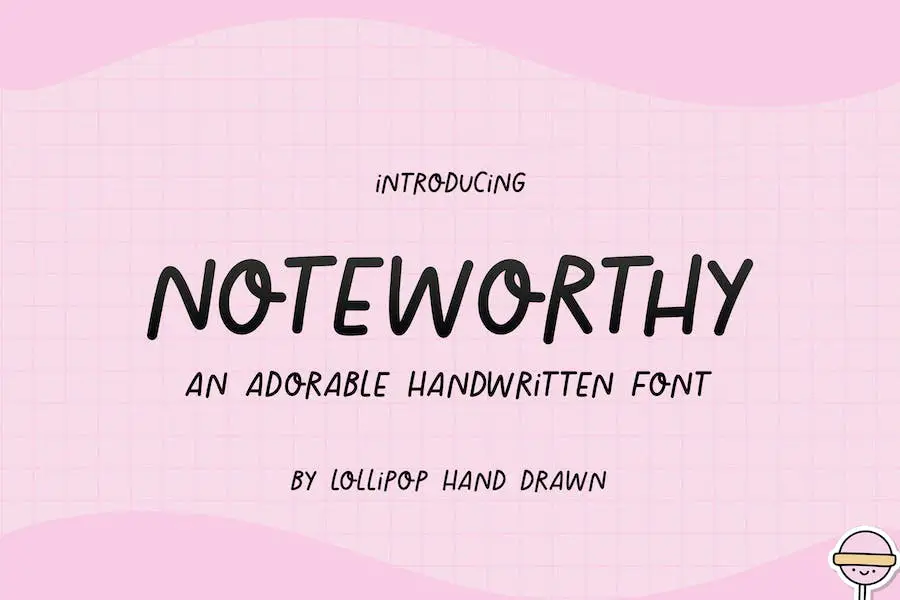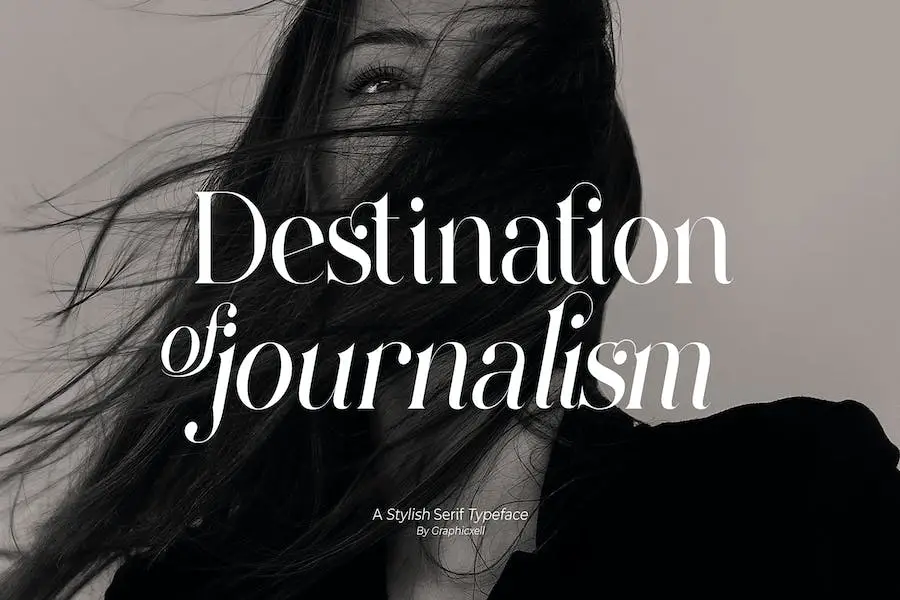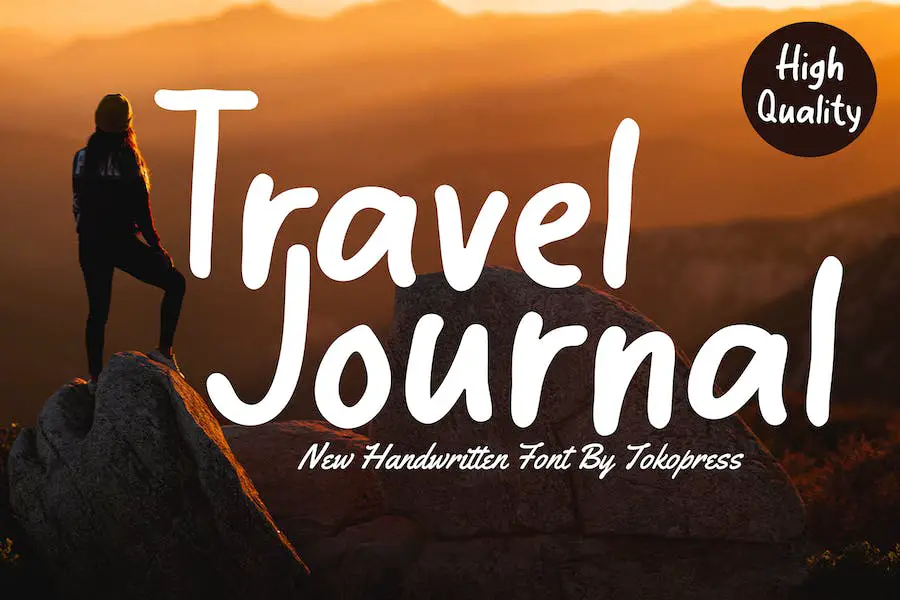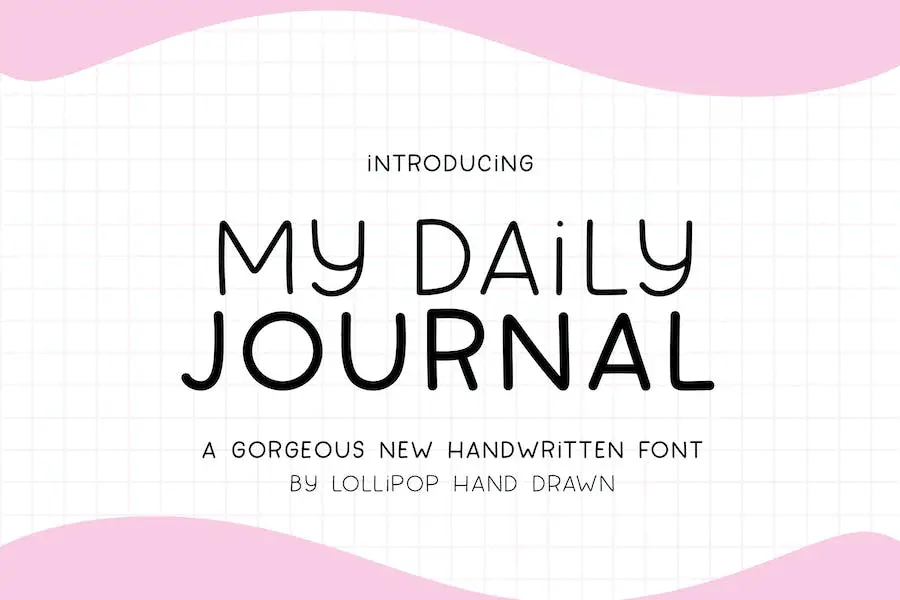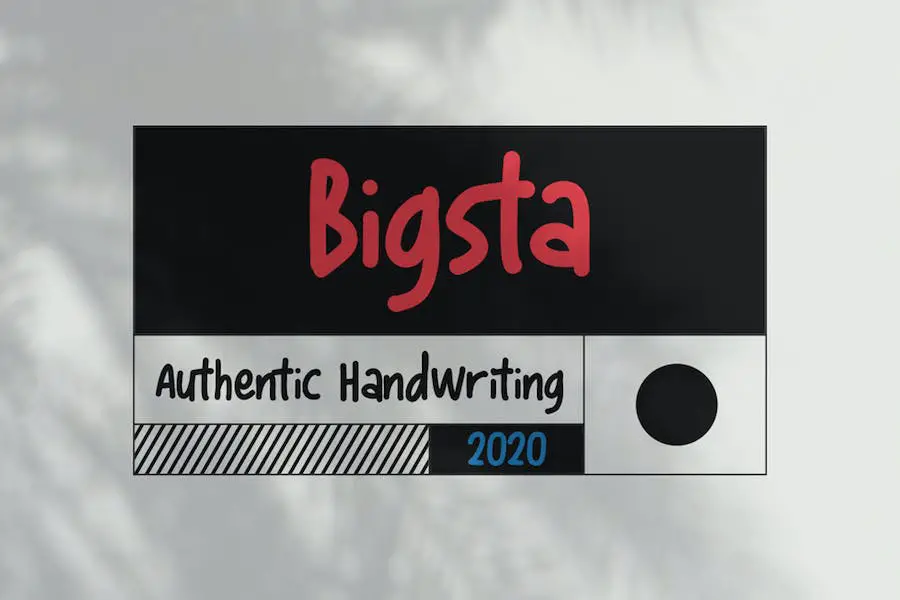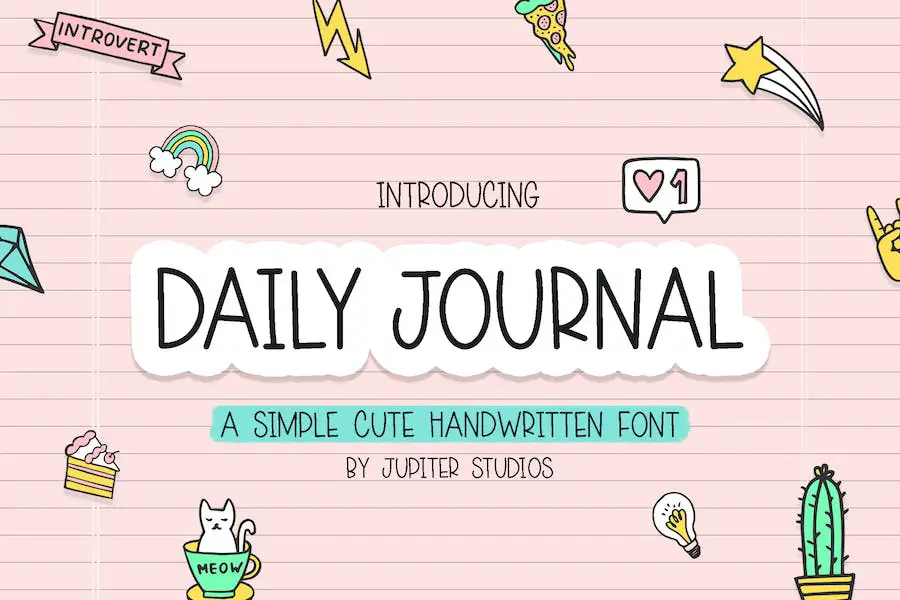
Cele mai bune 15 fonturi Bullet Journal 2023 (gratuit și premium)
Publicat: 2023-07-30Sunteți un designer grafic și doriți să îmbunătățiți designul proiectelor dvs. cu fontul perfect? Nu mai căuta! În această postare pe blog, vom explora cele mai bune 15 fonturi bullet journal care vă vor duce cu siguranță designurile la următorul nivel.
Dar mai întâi, s-ar putea să vă întrebați, ce face ca un font să fie „cel mai bun” pentru un jurnal bullet?
Ei bine, titlul acestei postări pe blog spune totul – cele mai bune 15 fonturi bullet journal! Și crede-mă, aceste fonturi nu sunt doar fonturile tale obișnuite. Au fost îngrijite și selectate cu atenție pe baza popularității, versatilității și atractivității lor estetice.
De fapt, știai că un font bine ales poate avea un impact semnificativ asupra designului general și lizibilitatea jurnalului tău bullet?
Statisticile și faptele sunt întotdeauna fascinante, așa că iată o mică informație pentru tine: conform unui sondaj recent, 87% dintre designerii grafici cred că tipografia joacă un rol crucial în succesul design-urilor lor.
Și odată cu popularitatea tot mai mare a jurnalului bullet, nu este de mirare că găsirea fontului perfect a devenit o prioritate de vârf pentru mulți designeri.
Acum că știți importanța alegerii fontului potrivit, să ne aruncăm în lista noastră cu cele mai bune 15 fonturi bullet journal. De la scripturi elegante și sofisticate până la sans serifuri îndrăznețe și moderne, avem un font pentru fiecare stil și preferință.
Așadar, fie că creați un spread săptămânal minimalist sau un tracker vibrant, veți găsi cu siguranță fontul perfect pentru a vă îmbunătăți experiența de jurnalizare bullet.
Cele mai bune fonturi Premium Bullet Journal
Îmbunătățiți designul bullet Journal cu aceste fonturi premium care vă vor duce proiectele la următorul nivel. Nu ratați să descoperiți fontul perfect pentru eforturile dvs. creative – explorați selecția de mai jos și deblocați posibilități infinite de design.
Melon Kundang
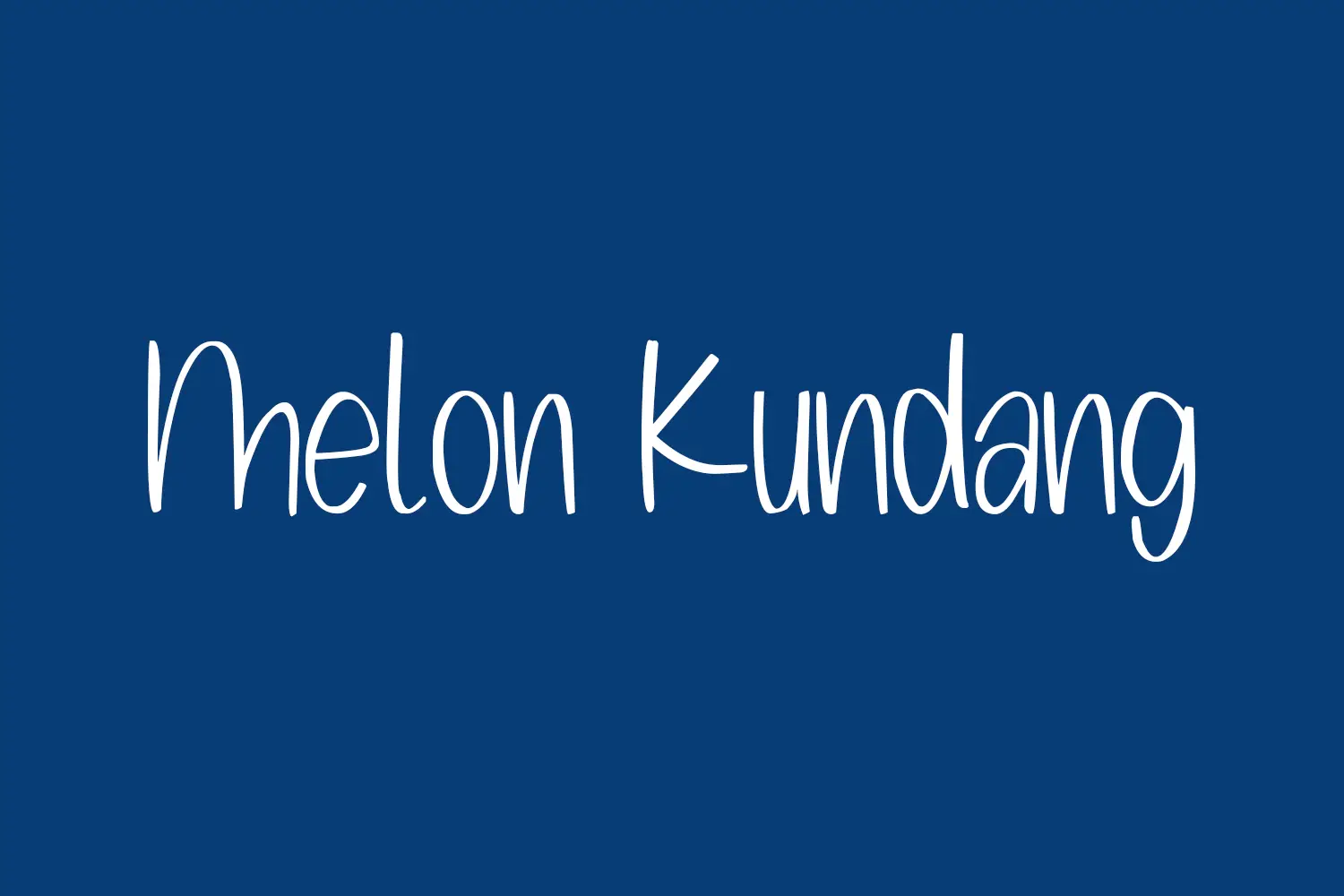
Melon Kundang este un font conceput special pentru designerii grafici care doresc să îmbunătățească designul proiectelor lor. Acest font drăguț bullet journal, creat de zamjump, adaugă o notă de personalitate și creativitate oricărui design.
Unul dintre atributele remarcabile ale Melon Kundang este natura sa jucăușă și capricioasă. Marginile rotunjite și curbele netede conferă acestui font o senzație prietenoasă și accesibilă, făcându-l perfect pentru proiecte uşoare sau adăugând o notă de farmec jurnalului tău.
Nu numai că Melon Kundang este atrăgător din punct de vedere vizual, dar este și foarte lizibil. Liniile curate și caracterele bine definite asigură că textul tău este ușor de citit, chiar și la dimensiuni mai mici.
Indiferent dacă îl folosiți pentru anteturi, paragrafe sau subtitrări, acest font se va asigura că conținutul dvs. este clar și captivant.
Palmiva
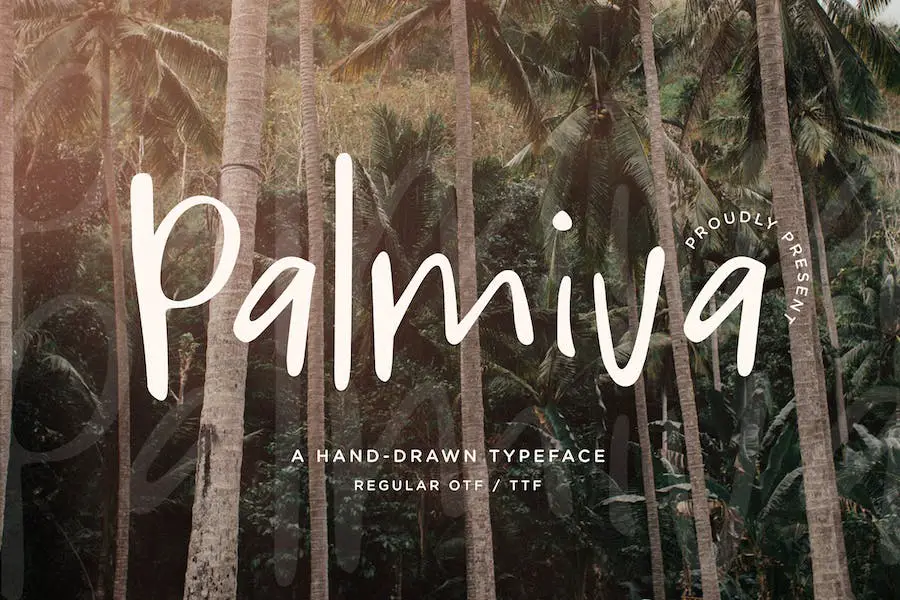
Palmiva este un font elegant desenat manual, care este creat cu atenție pentru a deveni un adevărat favorit pentru designerii grafici. Acest font este perfect pentru a adăuga o notă de eleganță și creativitate oricărui proiect.
Indiferent dacă lucrați cu fundaluri aglomerate sau aveți nevoie de un titlu remarcabil, Palmiva va arăta remarcabil și va îmbunătăți estetica generală a design-urilor dvs.
Stilul său unic și atenția la detalii îl fac o alegere de top pentru cei care doresc să-și ridice jurnalul bullet sau orice alt proiect de design. Cu Palmiva, munca ta va emana farmec și sofisticare, atrăgând fără efort atenția publicului tău.
Unic Tu
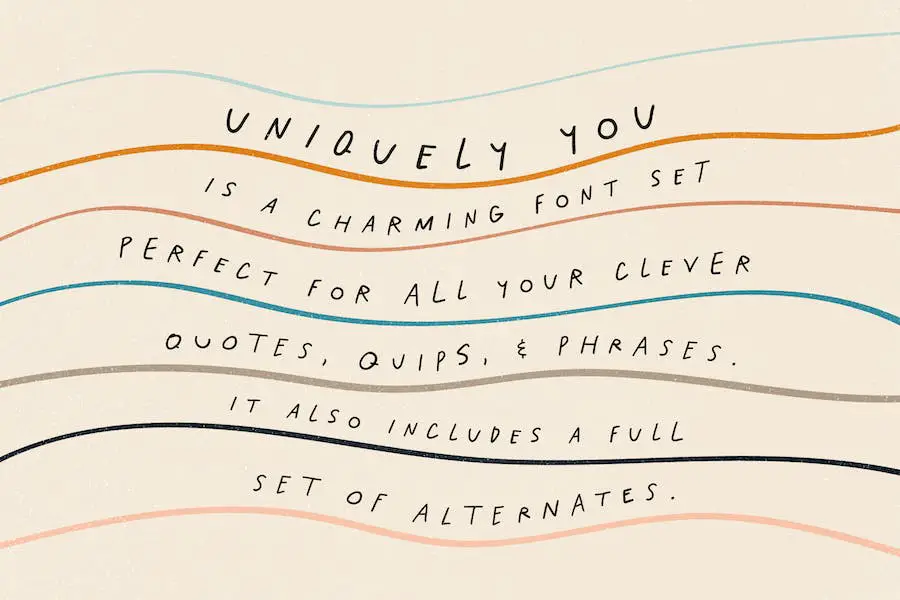
Uniquely You este un tip de literă jucăuș, desenat de mână, perfect pentru designerii grafici în căutarea unui font care să le ridice proiectele. Cu un set complet de alternative care pot fi amestecate și asortate, acest font permite o creativitate nesfârșită și asigură o estetică consecventă desenată manual în design-ul dvs.
Indiferent dacă lucrați la citate, invitații, felicitări, jurnale, artă de perete pentru camera copiilor sau orice alt proiect, Uniquely You vă va insufla design-urile cu o atmosferă jucăușă și distractivă. Ieșiți în evidență din mulțime și lăsați-vă creativitatea să strălucească cu acest font versatil și fermecător.
Notă simplă
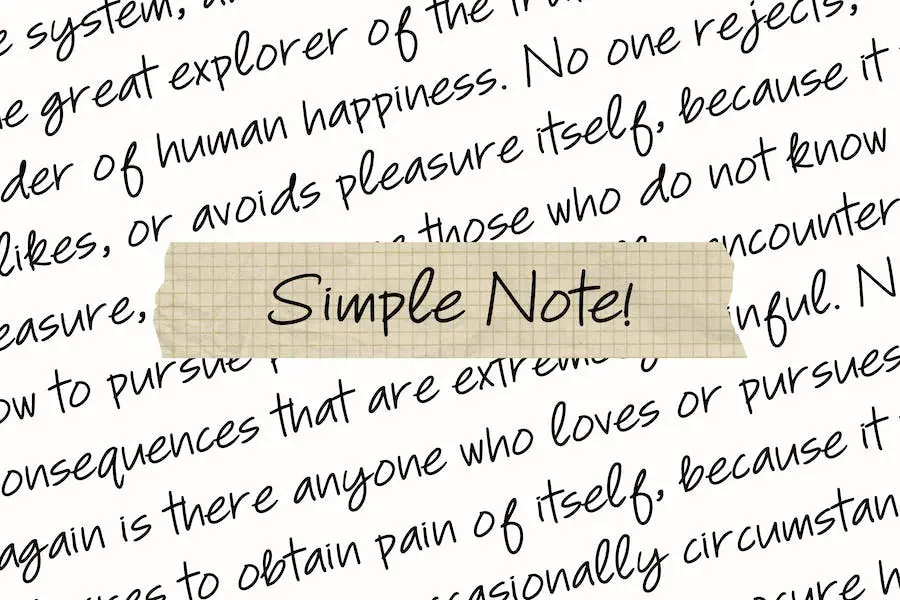
Simple Note este un font de scris de mână ocazional, care prezintă linii naturale, ceea ce îl face o alegere excelentă pentru diverse proiecte de design. Aspectul său relaxat și informal adaugă un fler unic notelor, descrierilor de produse, titlurilor, paragrafelor de produse, siglelor, mărcii și multe altele.
Cu designul său natural, Simple Note oferă o senzație scrisă de mână care adaugă o notă personală proiectelor tale. Indiferent dacă creați un jurnal bullet, proiectați descrieri de produse sau creați titluri captivante, acest font oferă o atmosferă relaxată și relaxată.
Versatilitatea Simple Note este unul dintre atributele sale remarcabile. Poate fi folosit într-o gamă largă de aplicații și proiecte de design, inclusiv note, titluri, descrieri de produse, logo-uri și material de branding.